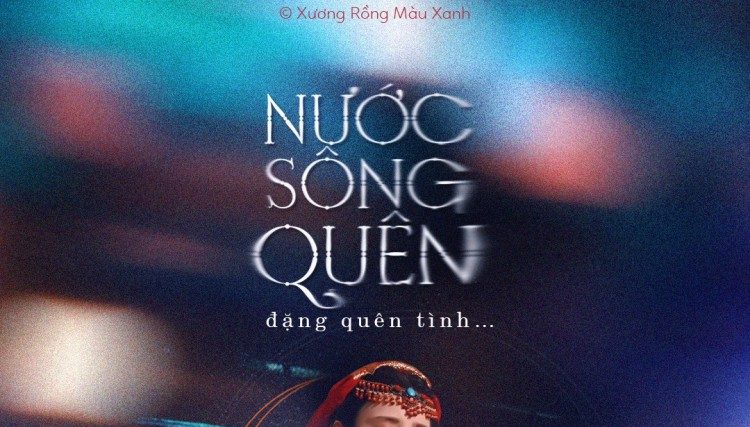
Giới thiệu về Font việt hóa MTD Francesca
Trong thế giới đồ họa hiện đại, việc tìm kiếm một Font Miễn Phí chất lượng luôn là ưu tiên hàng đầu của các bạn học sinh và giáo viên. Font việt hóa MTD Francesca là một bộ phông chữ mang phong cách thanh lịch, nhẹ nhàng nhưng không kém phần hiện đại. Được tối ưu hóa hoàn toàn cho bảng mã Unicode, bộ font này giúp người dùng dễ dàng soạn thảo văn bản tiếng Việt mà không lo gặp lỗi hiển thị ký tự hay dấu câu. Đây chính là giải pháp lý tưởng cho những ai yêu thích sự tinh tế trong từng nét chữ.
Những đặc điểm nổi bật của Font việt hóa MTD Francesca
Thiết kế sang trọng và tính ứng dụng cao
Font việt hóa MTD Francesca nổi bật với những đường nét uyển chuyển, tạo cảm giác chuyên nghiệp cho mọi tác phẩm nghệ thuật. Bộ chữ này rất phù hợp để làm tiêu đề báo cáo, thiết kế thiệp chúc mừng hoặc trang trí slide bài giảng trong nhà trường. Với sự kết hợp giữa nét thanh và nét đậm hài hòa, font chữ giúp nội dung truyền tải trở nên cuốn hút và dễ đọc hơn đối với người xem.
Kết luận về bộ phông chữ MTD Francesca
Việc sử dụng Font việt hóa MTD Francesca không chỉ làm tăng tính thẩm mỹ cho sản